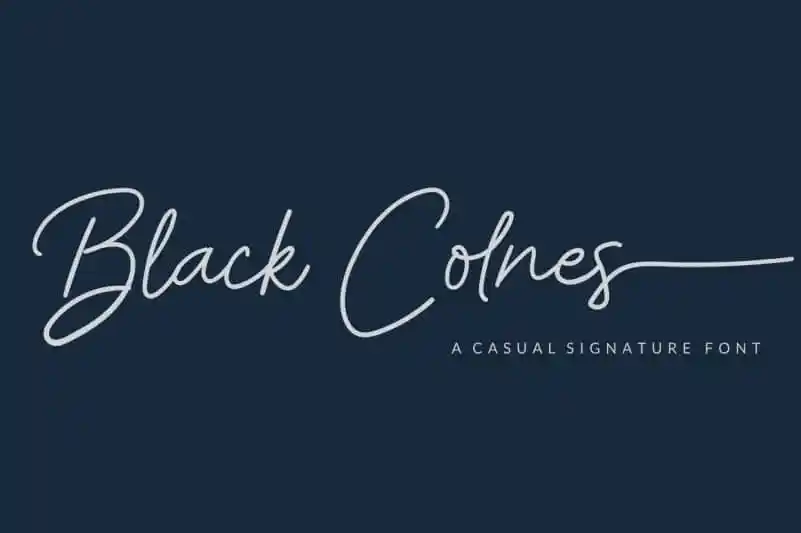
Black Colnes Handwritten Font – Download Grátis
Black Colnes Handwritten Font é uma fonte script autografada que captura a essência do estilo casual, elegante e sofisticado. Suave e envolvente ao mesmo tempo, esta fonte será perfeita para seus próximos projetos de design criativo. De carteirinha para capas de álbuns, cartões de visita à marcação em fotografias, Black Colnes vai levantar seu trabalho a um novo nível. Suave e moderna, essa font é ideal para personalizar suas mensagens com uma textura autografada única. Seja você designer gráfico ou amante da fotografia, este estilo elegante de letra escrita à mão certamente vai ajudá-lo a destacar seus trabalhos e projetos. Seja na criação de um simples quote ou em criar um design impressionante para sua cartela de cores, Black Colnes é uma escolha ótima que irá dar vida ao seu trabalho.